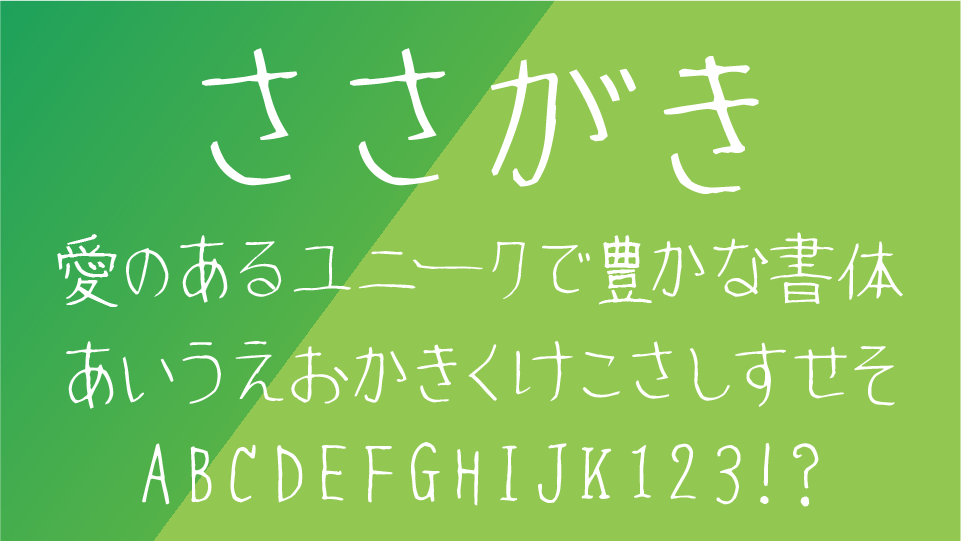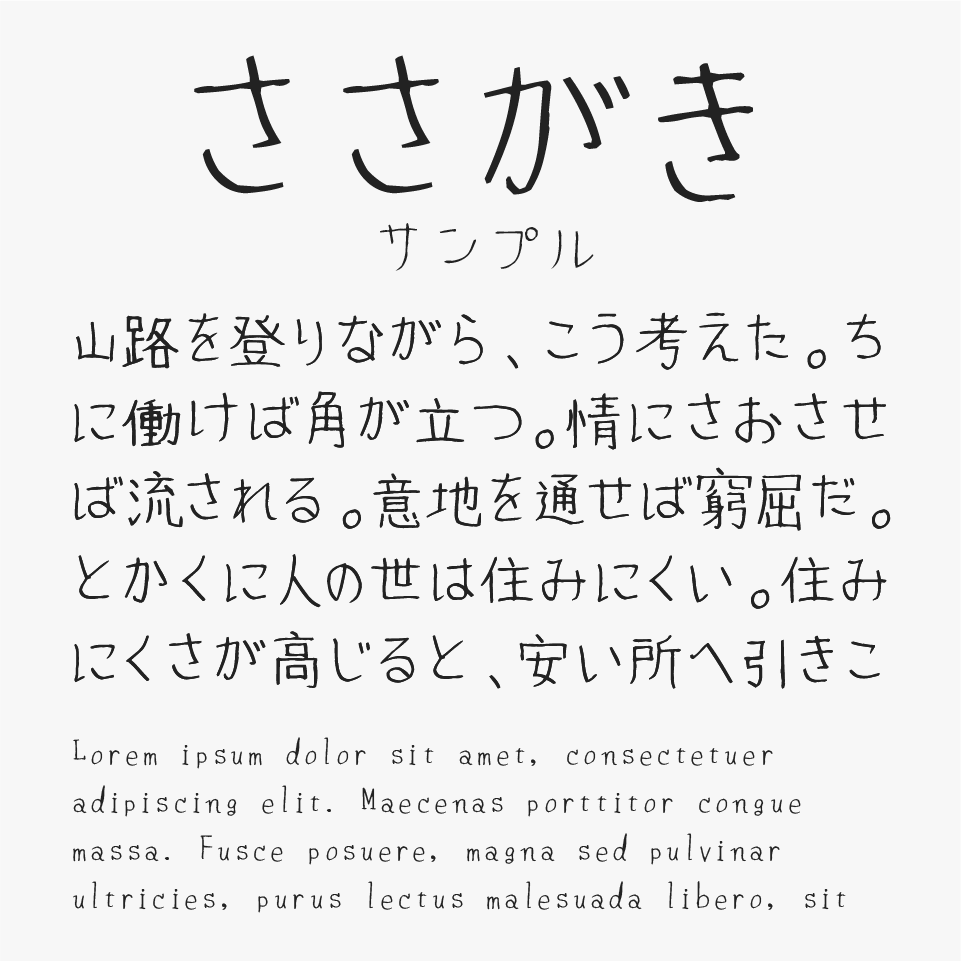
ささがきフォント
ささがきフォントは、ささっと落書きをしたような書き味の手書きフォントです。
ささっと落書きというテーマですが、崩れているわけではなく、無駄な装飾を抑えたシンプルな表情があり、素直で飾らない自然な雰囲気を感じさせます。手書きフォントらしい柔らかさを持ちながらも、全体は整いすぎずサラっと書いたようなラフに仕上げられており、静かで落ち着いた印象を与えてくれるフォントです。
控えめでやさしい印象を演出しやすく、エッセイ風デザインやブログアイキャッチ、カフェメニュー、同人誌、ライフスタイル系のSNS投稿などにぴったりなフォントです。
ささがきフォントを、ほかのラフでさらっとした雰囲気を持つ手書きフォントと比較してみると、自然な筆跡感と気取らない素朴さが特に魅力の手書きフォントです。